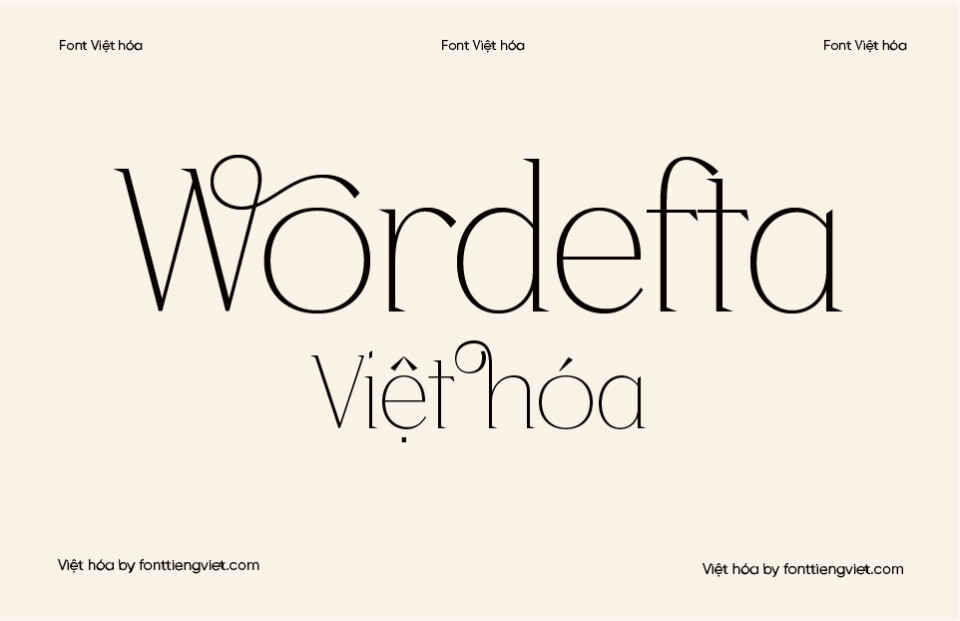
Font Việt hóa 1FTV VIP Wordefta
Trong thế giới thiết kế đồ họa hiện đại việc lựa chọn một bộ Font Miễn Phí chất lượng luôn là ưu tiên hàng đầu của các designer chuyên nghiệp. Một trong những cái tên đang gây bão trong cộng đồng sáng tạo tại Việt Nam chính là Font Việt hóa 1FTV VIP Wordefta. Đây không chỉ đơn thuần là một bộ font chữ mà còn là một tác phẩm nghệ thuật mang đậm phong cách tối giản thanh lịch và đầy hiện đại. Việc tìm kiếm và sở hữu phiên bản Việt hóa chuẩn chỉnh giúp người dùng dễ dàng ứng dụng vào các phần mềm soạn thảo văn bản hay thiết kế chuyên nghiệp mà không lo lỗi hiển thị dấu câu. Bài viết này sẽ giúp bạn hiểu rõ lý do vì sao bộ font này lại trở thành xu hướng hàng đầu hiện nay.
Đặc điểm nổi bật của Font Việt hóa 1FTV VIP Wordefta
Bộ Font Việt hóa 1FTV VIP Wordefta sở hữu những đường nét thanh thoát tinh tế tạo nên sự cân đối tuyệt vời cho mọi khung hình thiết kế. Điểm mạnh lớn nhất của nó chính là khả năng hiển thị tiếng Việt một cách mượt mà nhờ quá trình Việt hóa kỹ lưỡng từ đội ngũ 1FTV. Các ký tự có dấu như ă â ê ô ơ ư được điều chỉnh khoảng cách và tỷ lệ sao cho không phá vỡ cấu trúc nguyên bản của font gốc. Điều này cực kỳ quan trọng đối với các dự án đòi hỏi sự chuyên nghiệp và chỉn chu trong từng chi tiết nhỏ nhất.
Tính ứng dụng linh hoạt trong đa dạng lĩnh vực
Với phong cách hiện đại Font Việt hóa 1FTV VIP Wordefta cực kỳ phù hợp cho các thiết kế nhận diện thương hiệu. Bạn có thể sử dụng nó để làm logo danh thiếp hoặc bao bì sản phẩm cao cấp. Trong lĩnh vực truyền thông bộ font này giúp các bài đăng trên mạng xã hội như Facebook hay Instagram trở nên nổi bật và thu hút sự chú ý của khách hàng ngay từ cái nhìn đầu tiên. Ngoài ra đối với các bạn học sinh và giáo viên việc sử dụng font chữ này trong các bài thuyết trình PowerPoint sẽ tạo nên một giao diện trực quan sinh động và dễ tiếp cận hơn.
Lưu ý khi phối hợp font chữ trong thiết kế
Trong một bản thiết kế không nên sử dụng quá nhiều kiểu chữ khác nhau gây rối mắt. Bạn hãy thử kết hợp Font Việt hóa 1FTV VIP Wordefta với một font không chân (sans-serif) đơn giản để tạo sự tương phản. Sự phối hợp này giúp phân cấp thông tin rõ ràng từ tiêu đề đến nội dung chi tiết giúp người đọc dễ dàng theo dõi mạch văn bản. Đặc biệt khi in ấn bạn nên kiểm tra kỹ kích thước chữ để đảm bảo các nét mảnh của font vẫn giữ được độ sắc nét và không bị nhòe.
Kết luận về giá trị của Font Việt hóa 1FTV VIP Wordefta